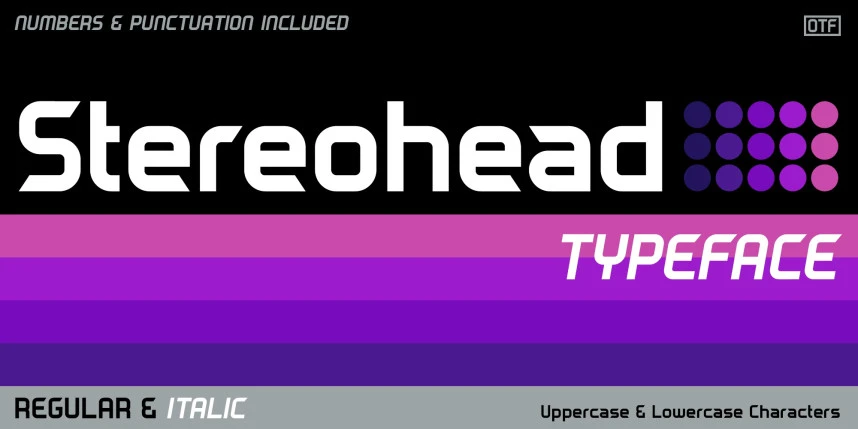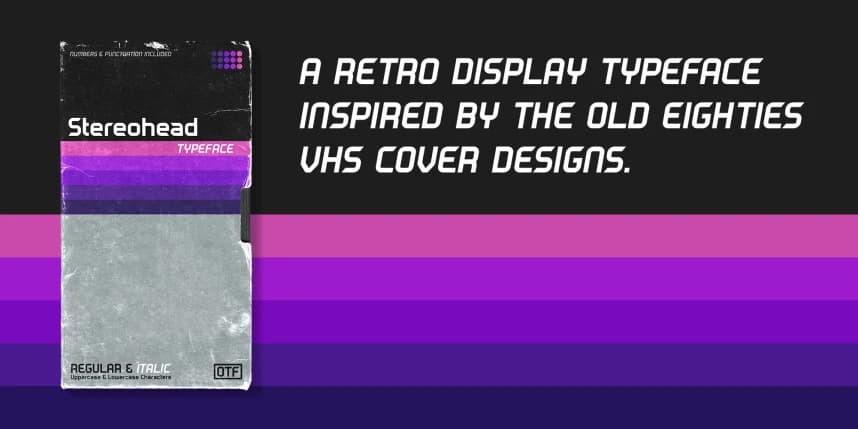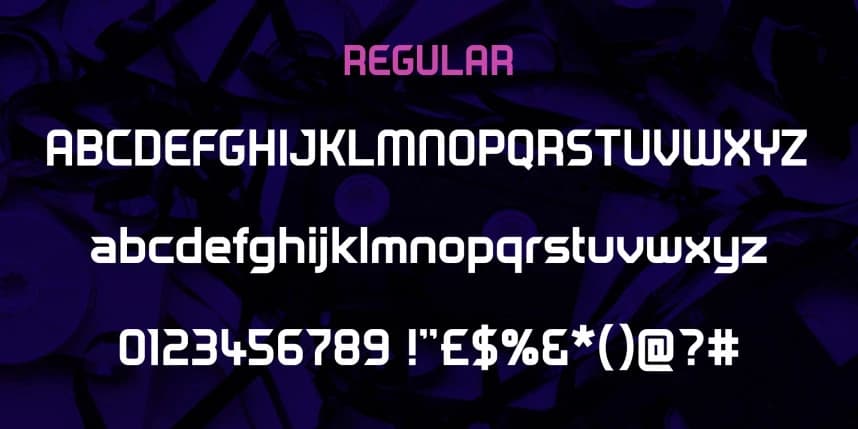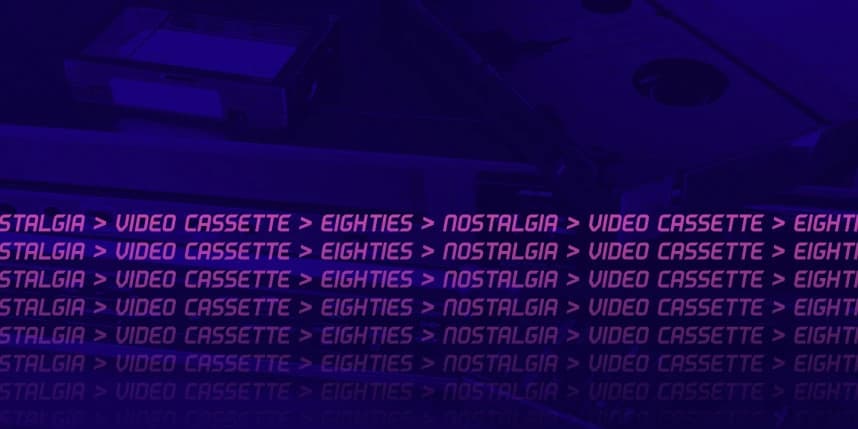
Stereohead Font
Stereohead Font, eski 80'ler video kaset kapak tasarımlarından ilham alan retro bir sans-serif gösterim tipi yazı tipidir. Bu yazı tipi, dergi başlıklarında, tişört tasarımlarında, posterlerde, ambalajlarda ve reklam amaçları için mükemmel bir şekilde kullanılabilir.
Stereohead Font, eski 80'ler video kaset kapak tasarımlarından esinlenen retro bir sans serif gösterim yazı tipidir. Bu yazı tipi, dergi başlıklarında, tişört tasarımında, posterlerde, ambalajlarda ve reklam amaçları için mükemmel bir şekilde kullanılabilir.
Stereohead
Stereohead Regular